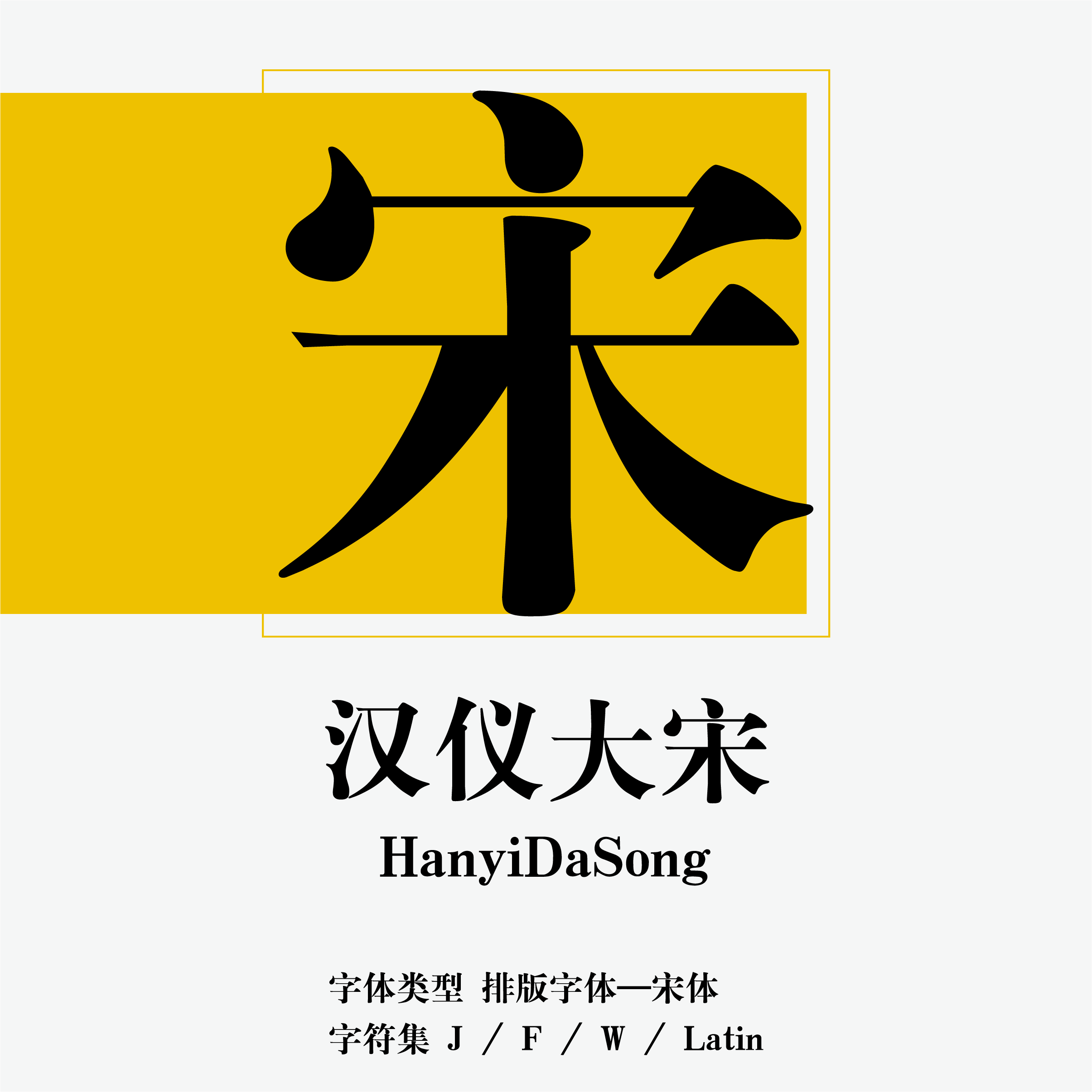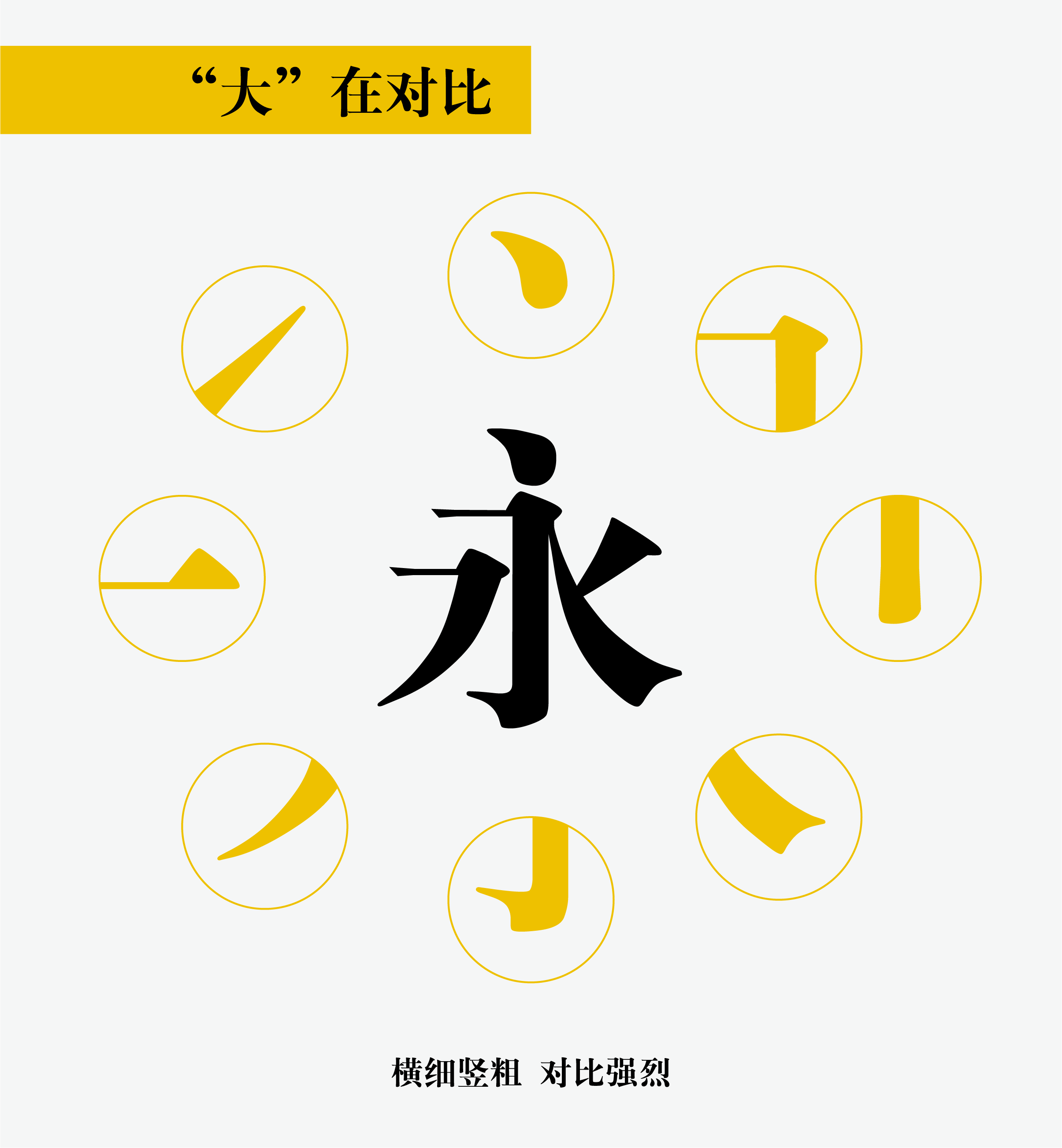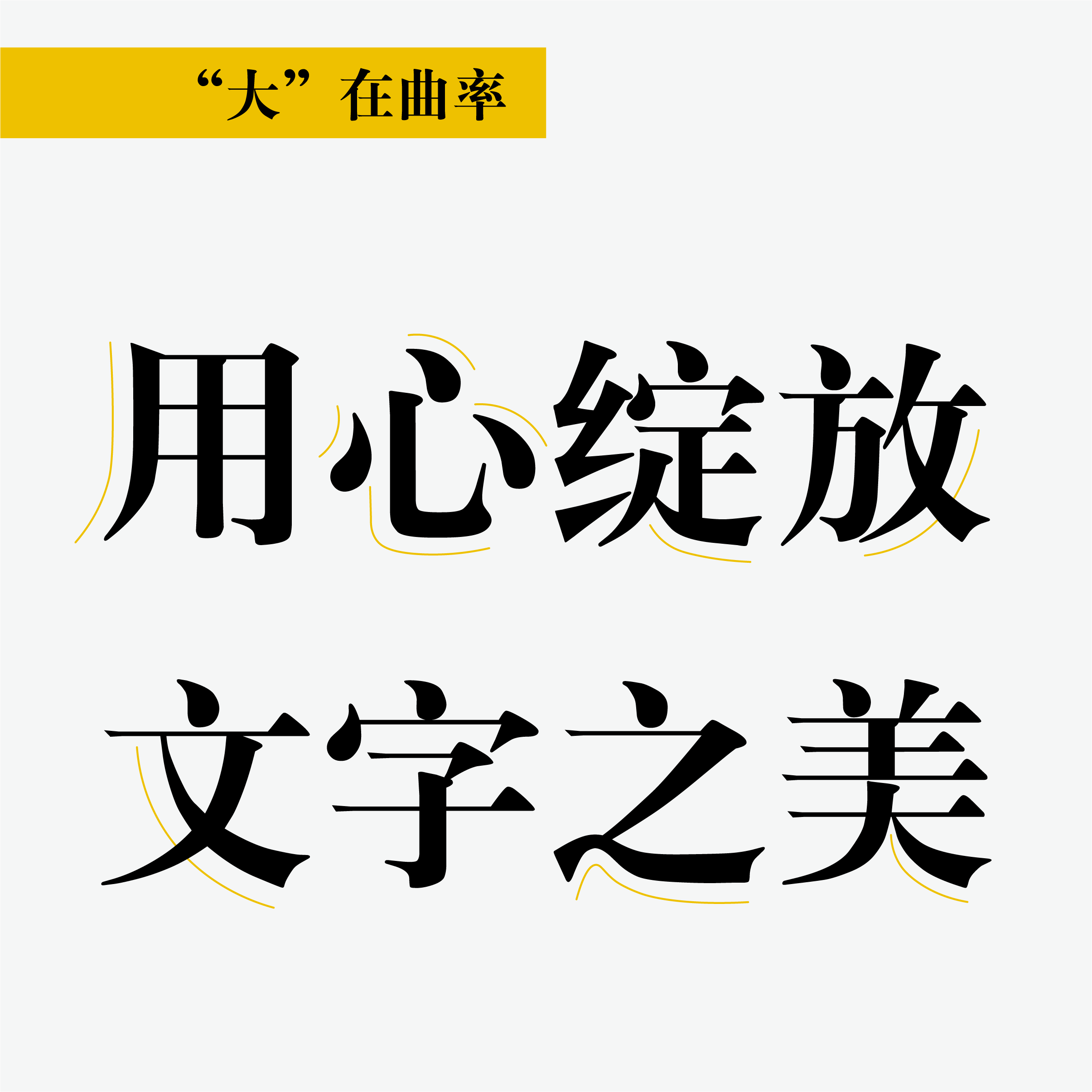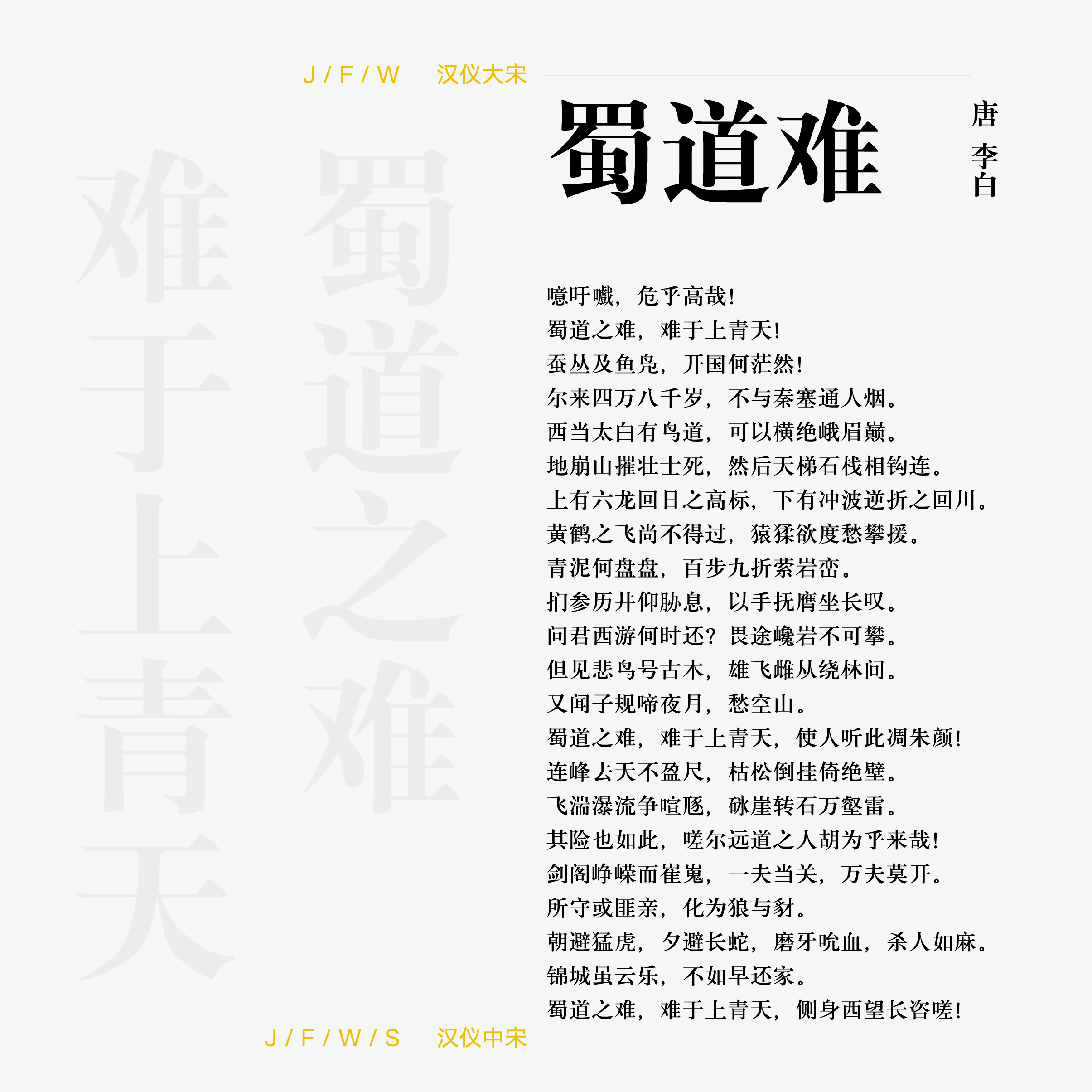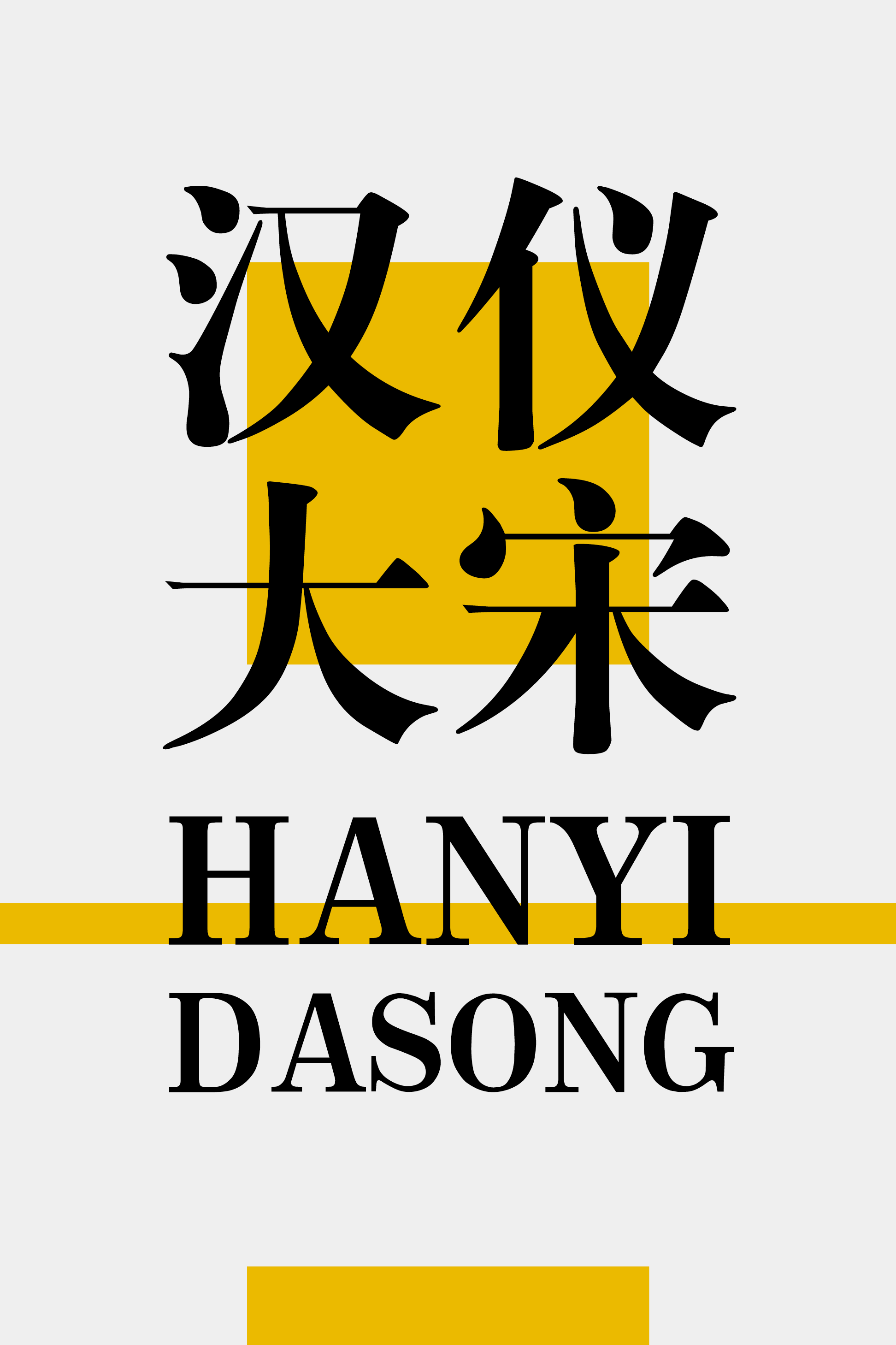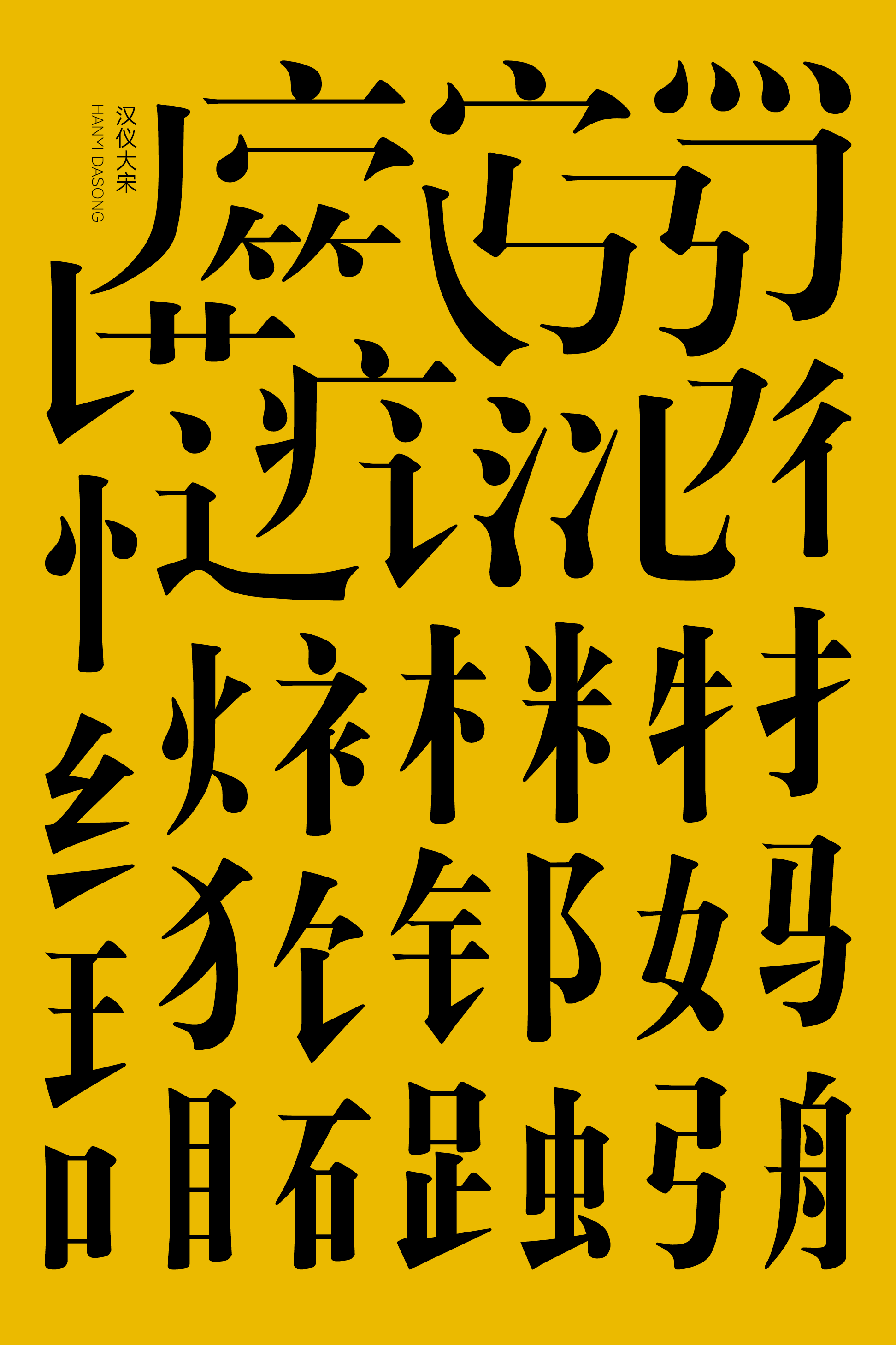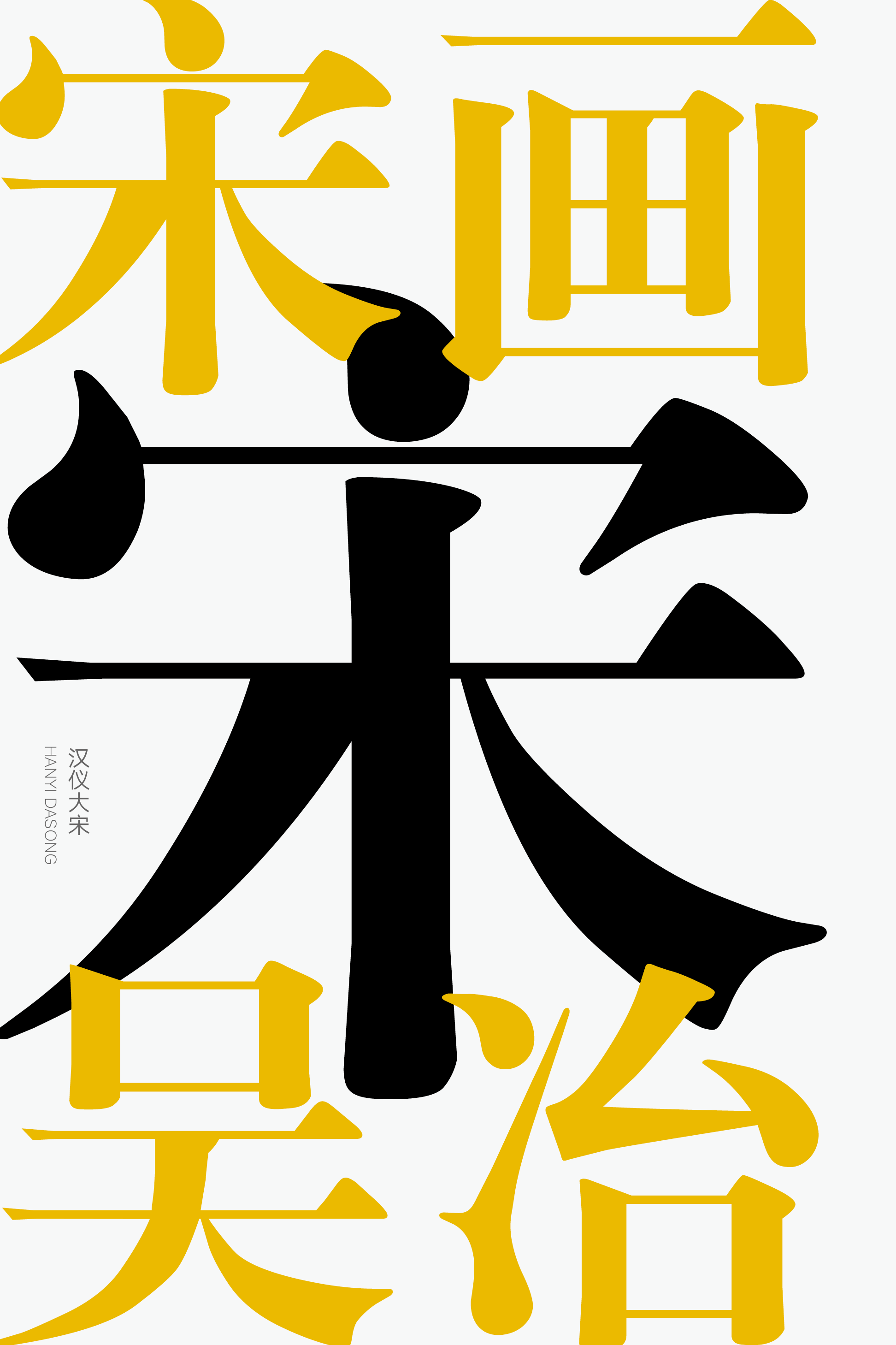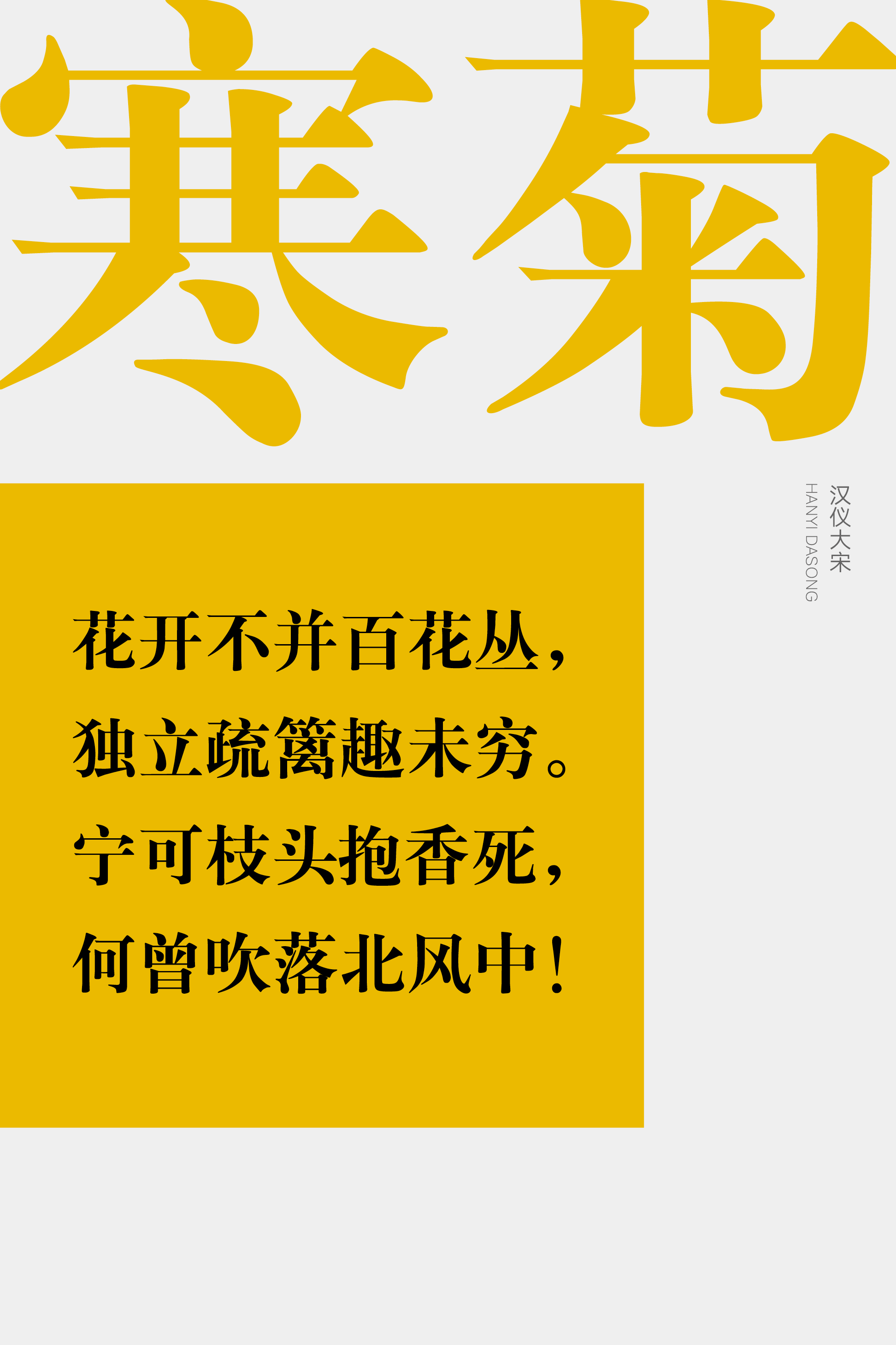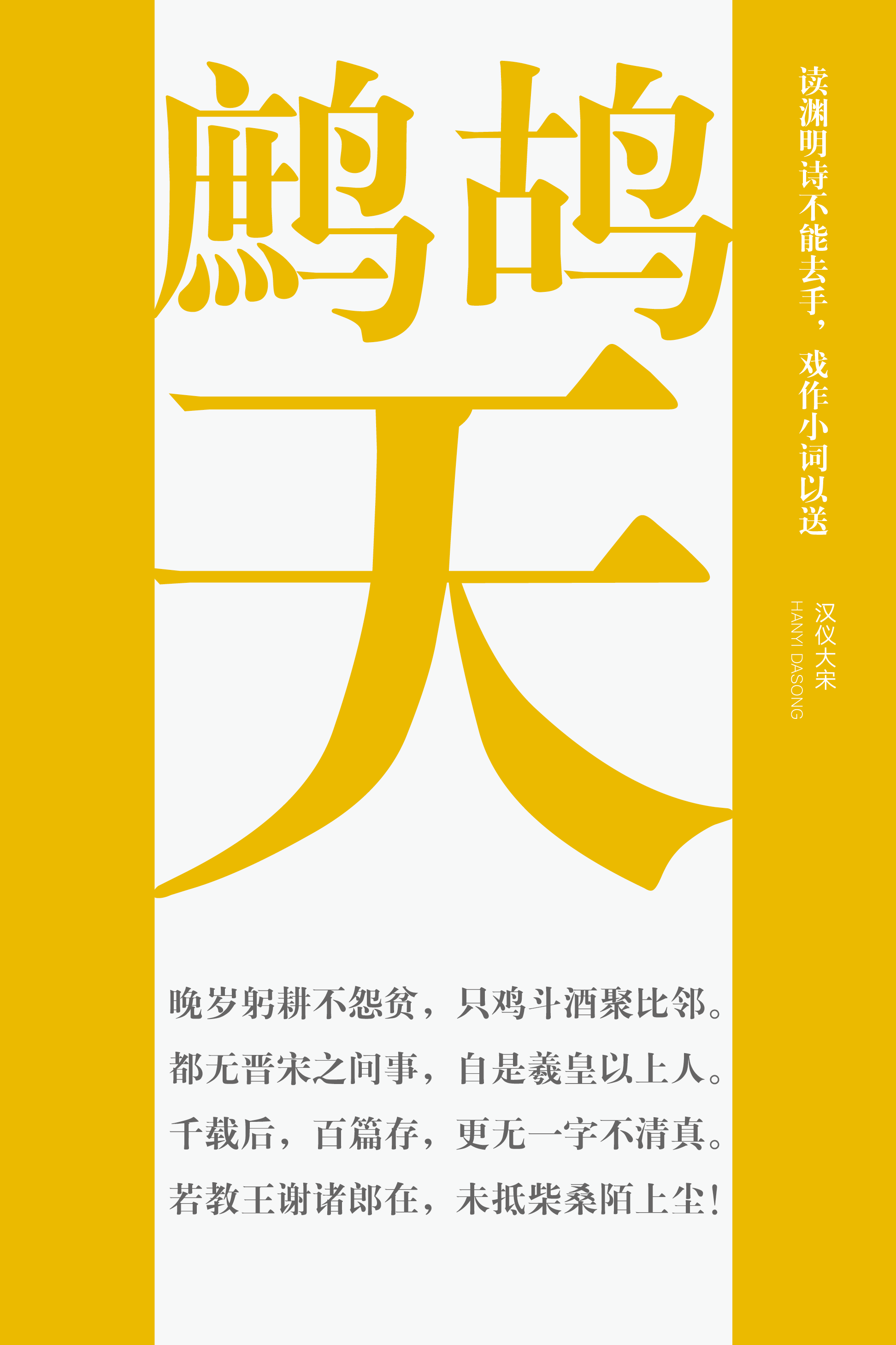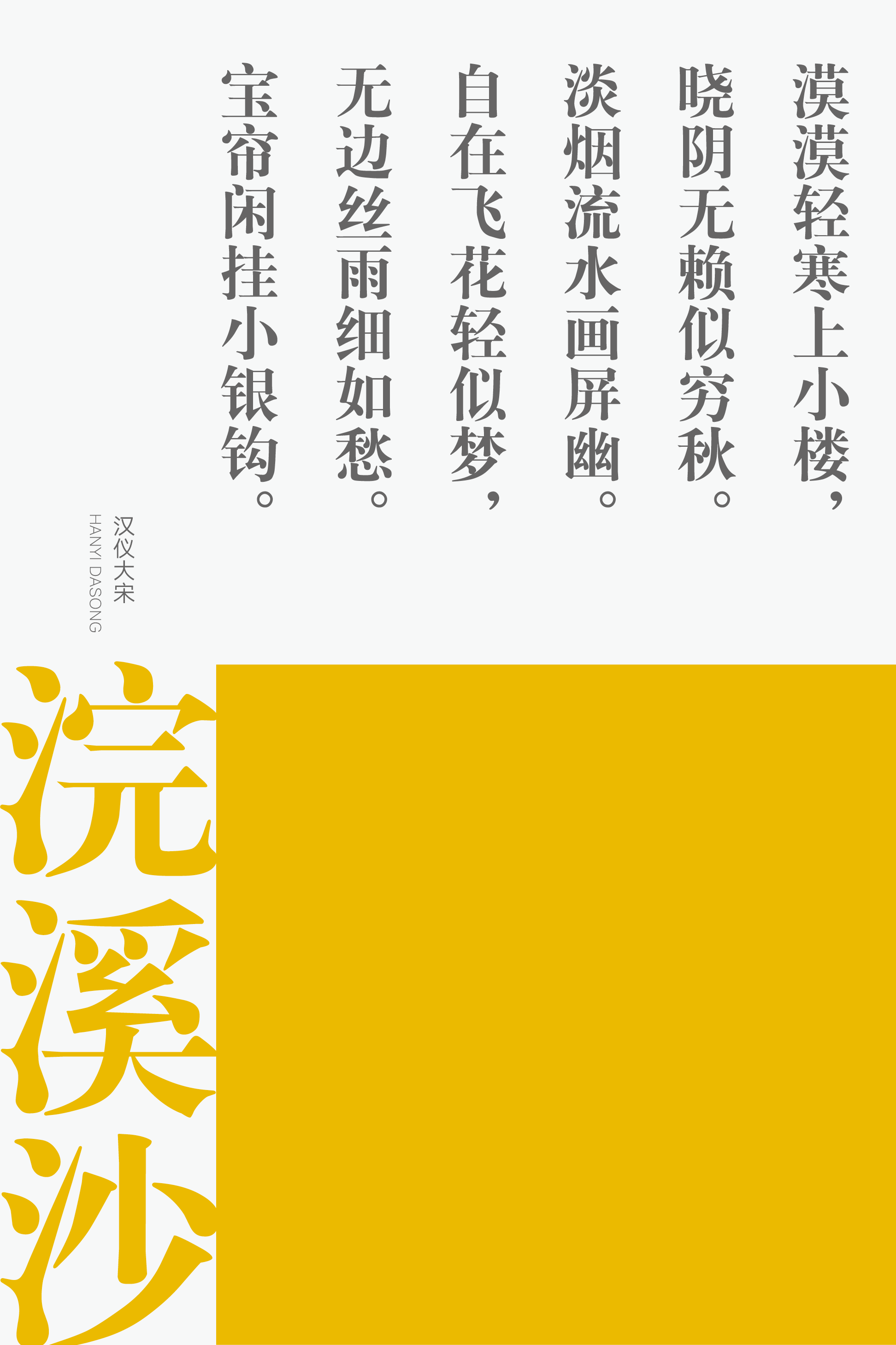
汉仪大宋
汉仪大宋,严肃大方、端正平稳,字形方而正,笔画粗细对比强烈。汉仪大宋之“大”在于字面、在于对比、在于曲率,是一款适合应用于标题的排版宋体,克制而严谨,适合书籍封面、影视标题以及较为正式严肃的使用场景,推荐与更适合正文排版的汉仪中宋(S字符集可全面满足出版物的排版需求)搭配使用。
汉仪大宋|字体特征
汉仪大宋,字形方而正,字面宽博。
笔画粗细对比强烈。
线条的曲率大而优美。
汉仪大宋适合应用于标题排版,推荐与更适合正文排版的汉仪中宋(拓展至 S 字符集,符合 GB18030-2022 标准,实现级别 2,可全面满足出版物的排版需求,包含 27780 个汉字字符)搭配使用。
汉仪大宋|字体样张